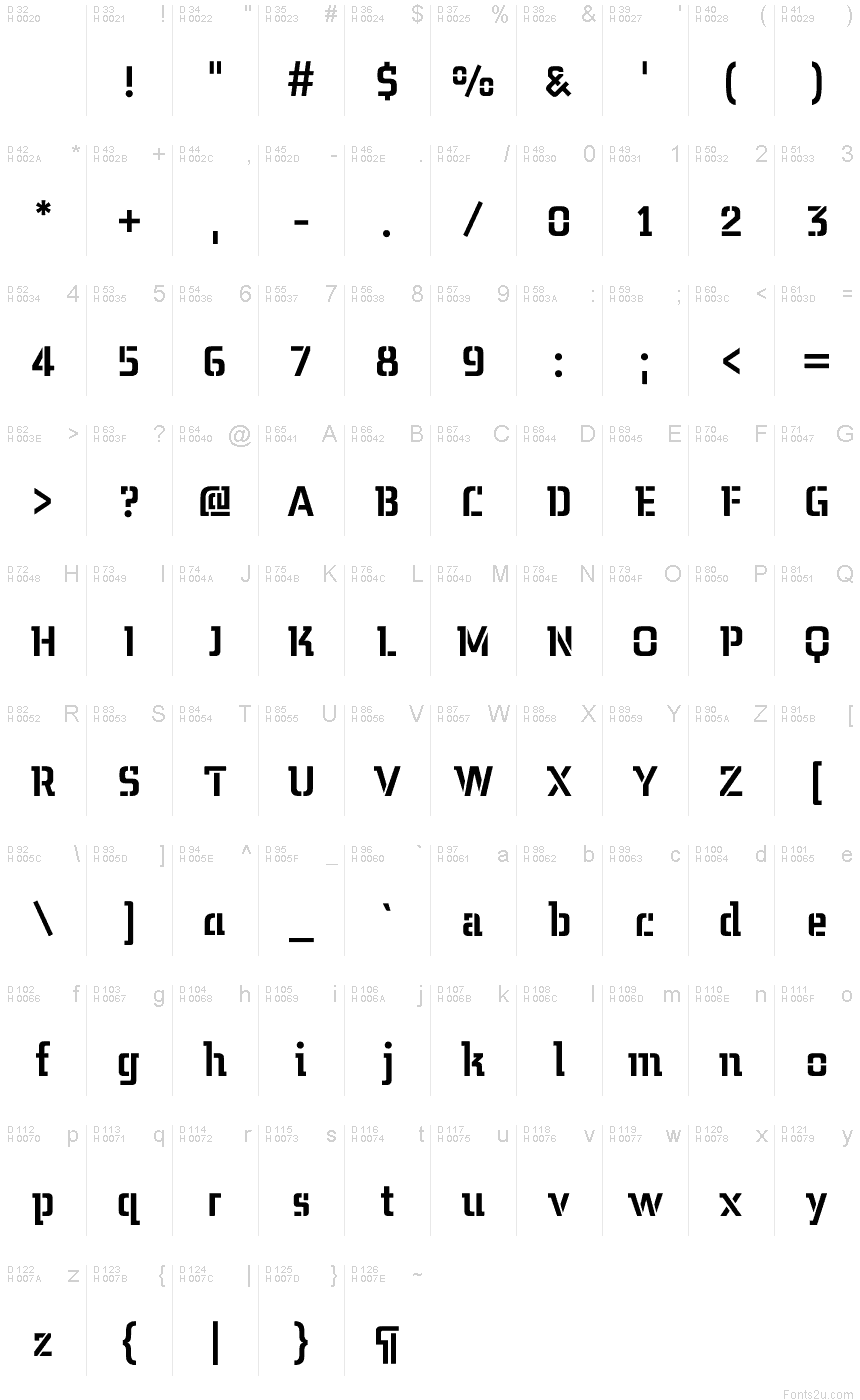
Midnight Kernboy Stencil من تصميم James Arboghast هو خط عرض (display font) مجاني بأسلوب "الستنسل"، يحوّل أي كلمة إلى تصميم ميكانيكي جريء. بفضل حروفه الطويلة والمدمجة، وأكتافه المربعة، وفراغات الستنسل النظيفة، يبدو الخط وكأنه قُصَّ من ألواح معدنية، ومع ذلك تمنحه الانحناءات الطفيفة والضربات الزاوية طابعاً سريعاً وحيوياً بعيداً عن الجمود. إيقاع الخط العام مضغوط وقوي، مما يجعله مثالياً للعناوين التي تحتاج إلى مظهر التحذيرات المطبوعة أو الملصقات الصناعية.
استخدم Midnight Kernboy Stencil لإضفاء طابع خشن وجريء على إصدارات أزياء الشارع (streetwear)، وسلاسل الملصقات، وإعلانات النوادي، والتغليف، وعناوين الألعاب، وأغلفة الألبومات الموسيقية ذات الطابع القوي. يتألق هذا الخط المجاني في النصوص الكبيرة ذات التأثير العالي، حيث تصبح فراغات الستنسل عناصر تصميم جرافيكية بحد ذاتها. عند استخدامه في أحجام أصغر، قم بدمجه مع خط "سانس سيريف" (sans serif) بسيط للحفاظ على سهولة القراءة في التصميم، واترك عائلة Midnight Kernboy تتولى مهمة العناوين الصارخة والمليئة بالشخصية.